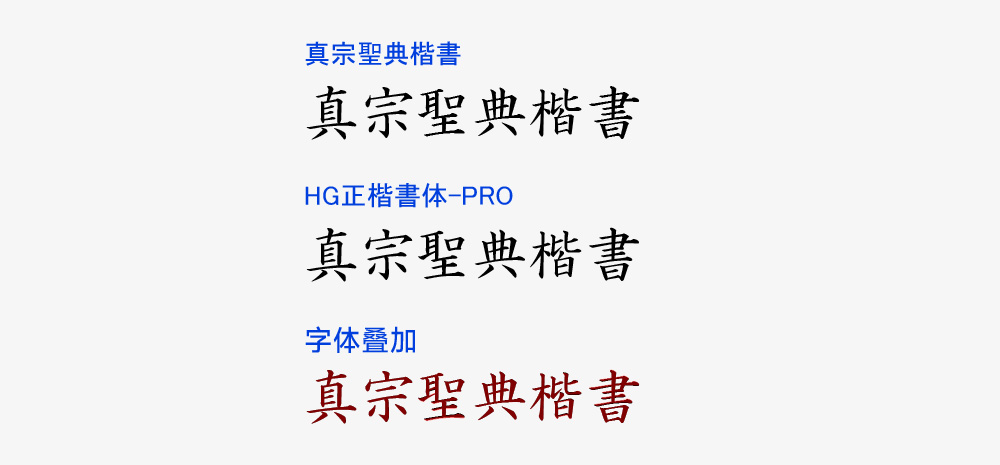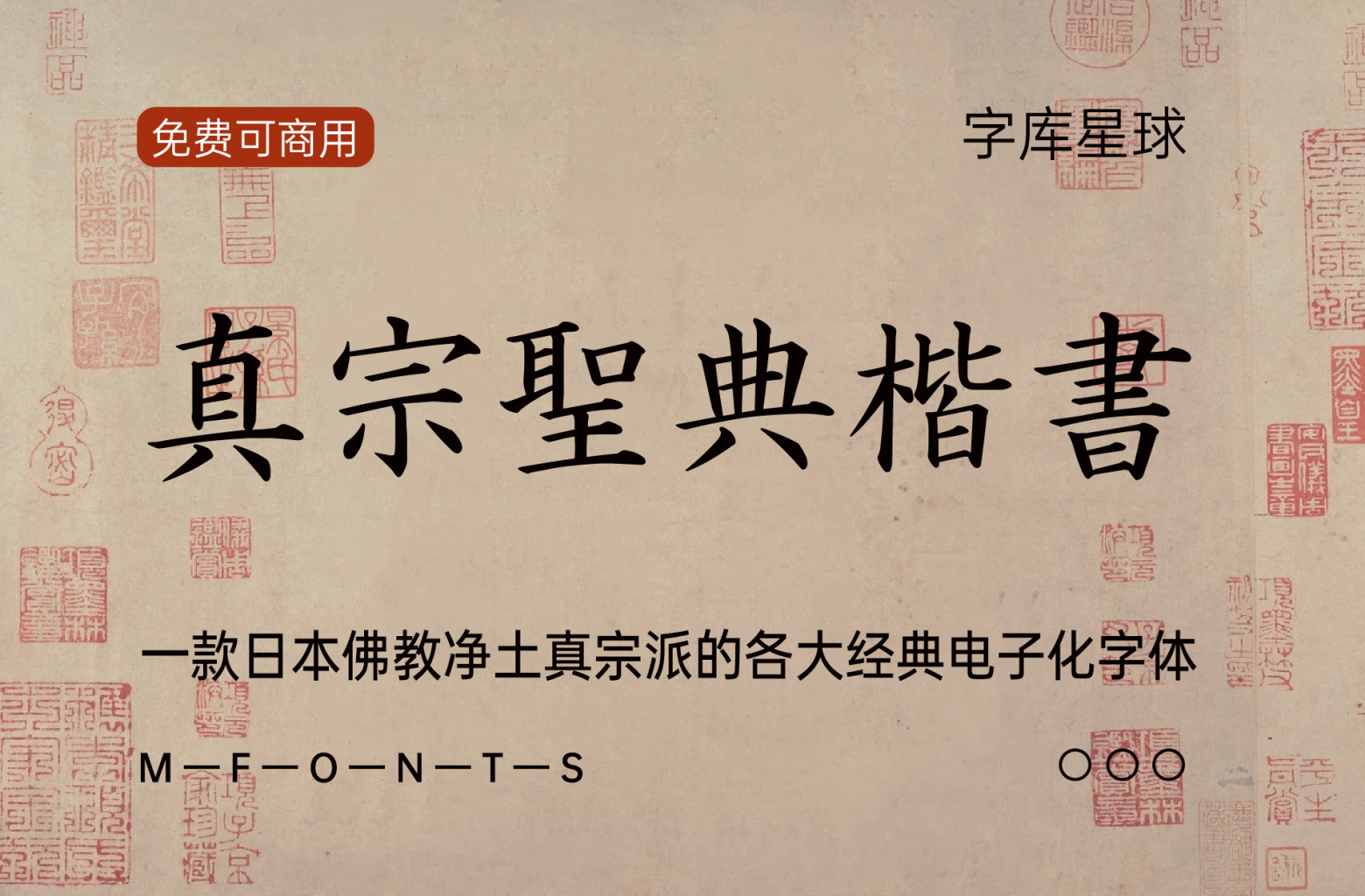
真宗圣典楷书
特别提醒:这个字体疑似是直接使用HG正楷書体-PRO改了个名称,而HG正楷書体-PRO的版权归属是RICOH,这个字体有极高的侵权风险,不建议商用!
下面是真宗圣典楷书与HG正楷書体-PRO的比对图,不能说极为相似,只能说一模一样,请大家注意侵权风险。
真宗圣典楷书是日本“净土真宗圣典”系列字体的其中一款。这个字体是为了将日本佛教「净土真宗派」的各大经典电子化而开发的字体,字体字形还原原书,颇具旧时楷书风韵。